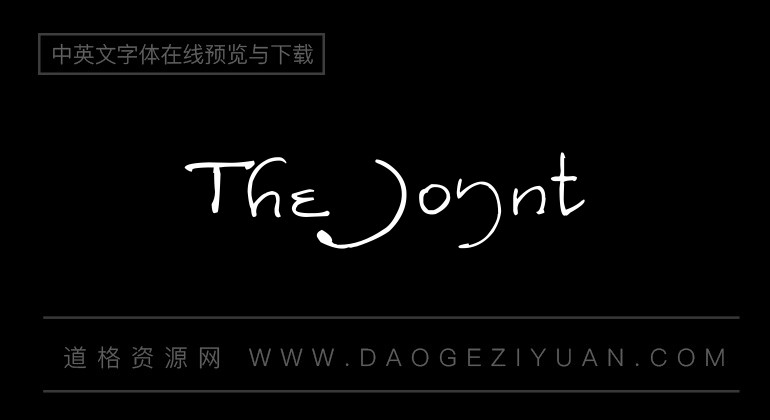
The Joynt 是一种现代手写风格的字体,由英国设计师 Laura Worthington 创造。该字体在2012年被发布,它的设计灵感来源于手写的招牌和海报,有着明显的卡通风格,同时也具有一些独特的装饰性元素。 这种字体的特点是线条圆润、柔和,字母间距相对较宽,适合用于大标题、标志和海报等设计项目。The Joynt 还包含多种字形变体,包括一些独特的装饰元素,让设计师能够自由地探索创造出更多的设计效果。内容介绍
The Joynt是一款非常不错的手写艺术字体,具有很好的视觉感,适合于文化类的宣传设计、商业类品牌的广告和产品包装设计以及个性化文字排版等较多场景。